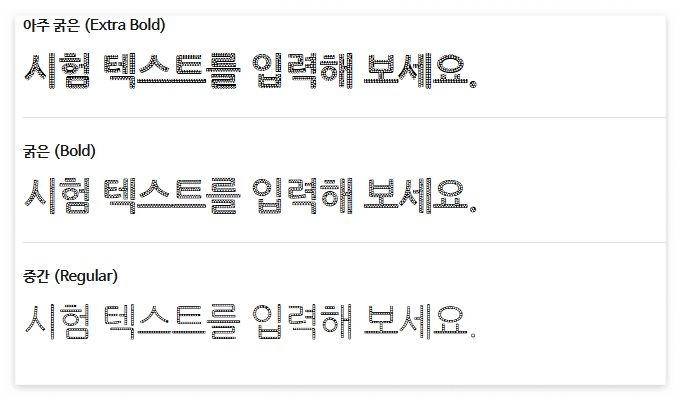
나눔고딕 에코는 네이버가 제공하는 특별한 글꼴로, 잉크 절약과 환경 보호를 고려하여 설계된 서체입니다.
출력 시 잉크 사용량을 최대 35%까지 절감할 수 있으며, 이산화탄소 배출 감소에도 기여합니다.
나눔고딕 에코 - 잉크 절약과 환경 보호를 동시에 실현하는 무료 글꼴
나눔고딕 에코의 특징과 장점
나눔고딕 에코는 단순히 출력 효율성을 높이는 것을 넘어, 환경 보호를 위한 작은 실천을 가능하게 하는 독창적인 글꼴입니다.
1. 잉크 절약 효과
나눔고딕 에코는 글자 내부에 미세한 구멍이 뚫려 있어 잉크 사용량을 최대 35%까지 줄일 수 있습니다.
출력 시 잉크가 구멍 주위로 번지며 빈 공간이 자연스럽게 채워지기 때문에, 텍스트의 가독성을 유지하면서도 잉크 소비를 줄이는 데 효과적입니다.
2. 환경 보호 기여
잉크 절약은 단순히 비용 절감 이상의 의미를 가집니다.
1년에 1,000만 개 이상 폐기되는 잉크 카트리지를 줄이고, 잉크 제조 과정에서 발생하는 이산화탄소 배출량도 감소시킵니다.
작은 선택으로 지구 환경 보호에 기여할 수 있는 친환경 글꼴입니다.
3. 다양한 굵기와 크기 제공
나눔고딕 에코는 Extra Bold, Bold, Regular 세 가지 굵기를 제공하며, 이를 통해 문서의 제목부터 본문까지 유연하게 활용할 수 있습니다.
4. 한글과 영문 혼합 문서에 적합
나눔고딕 에코는 한글 2,350자와 영문 94자, KS 약물 985자를 지원합니다.
한글과 영문이 혼합된 문서에서도 자연스러운 디자인을 유지하며, 다양한 문서 작업에 적합합니다.
나눔고딕 에코의 활용 방안
1. 문서 출력 비용 절감
기업이나 학교에서 대량 문서를 출력하는 경우, 나눔고딕 에코를 사용하면 잉크 사용량을 크게 줄일 수 있습니다.
이는 출력 비용 절감은 물론, 대규모 환경 보호에도 기여합니다.
2. 보고서 및 발표 자료 작성
나눔고딕 에코의 세 가지 굵기를 활용하면 제목과 본문에 적합한 서체를 선택해 깔끔하고 전문적인 문서를 작성할 수 있습니다.
특히, 보고서나 발표 자료에서 강조할 부분에 Bold나 Extra Bold를 사용하면 효과적입니다.
3. 학교 및 공공기관의 친환경 정책 지원
학교, 도서관, 공공기관 등 잉크 사용량을 줄이려는 친환경 정책을 시행하는 곳에서 나눔고딕 에코는 완벽한 대안이 됩니다.
학생들의 출력 작업, 기관의 공문 작성 등에 활용하면 좋은 사례가 될 수 있습니다.
나눔고딕 에코 사용 후기
나눔고딕 에코를 사용해보면, 출력된 문서의 가독성이 유지되면서도 잉크 절약 효과가 뛰어나다는 점을 바로 느낄 수 있습니다.
일반 글꼴과 비교했을 때 육안으로는 큰 차이를 느끼기 어렵지만, 실제 잉크 사용량과 관련된 비용 절감 효과는 분명합니다.
특히, 친환경적인 가치에 공감하는 사용자들에게 좋은 반응을 얻고 있으며, 많은 기업과 공공기관에서 출력 환경 개선을 위해 이 글꼴을 채택하고 있습니다.
마치며
나눔고딕 에코는 단순히 글꼴 이상의 가치를 제공합니다.
잉크 절약, 비용 절감, 환경 보호라는 세 가지 요소를 동시에 실현하는 혁신적인 서체로, 개인과 조직 모두에게 유용한 선택이 될 것입니다.